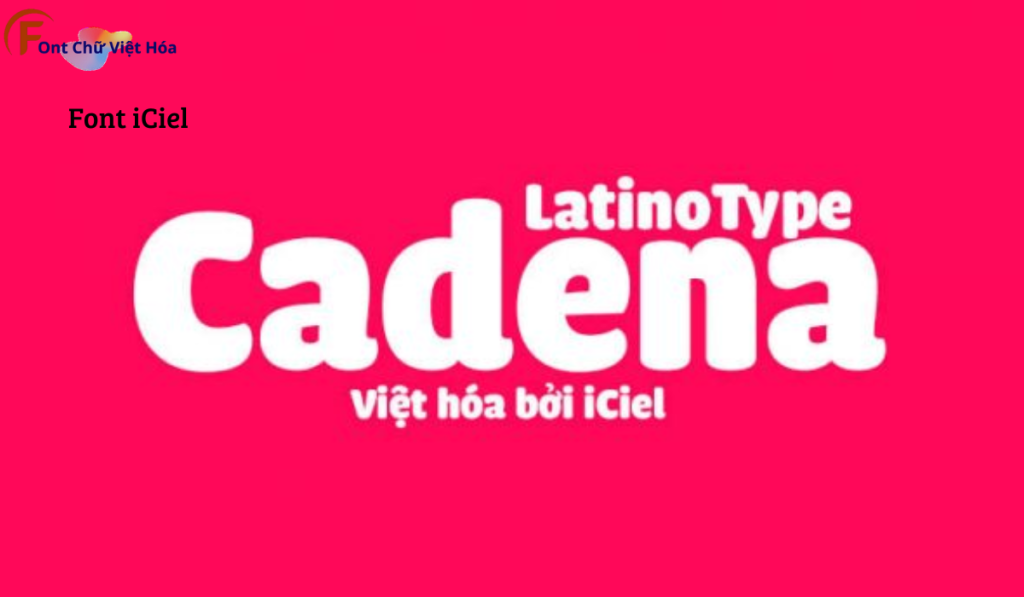
Font iCiel Cadena Việt Hóa
Bộ Font: iCiel
Phân loại: Cá tính, Độc đáo
Font iCiel Cadena Việt Hóa, thuộc bộ font iCiel, là font sans-serif hiện đại, nổi bật với các nét chữ rõ ràng và độ dày đa dạng. Font này có các đường nét mạnh mẽ, dễ đọc, tạo cảm giác hiện đại và chuyên nghiệp. Font iCiel Cadena Việt Hóa lý tưởng cho các dự án thiết kế như poster, logo, và bao bì sản phẩm. Việc Việt hóa font giúp người dùng dễ dàng tích hợp vào các thiết kế tiếng Việt, mang lại sự tiện lợi và nâng cao tính thẩm mỹ.